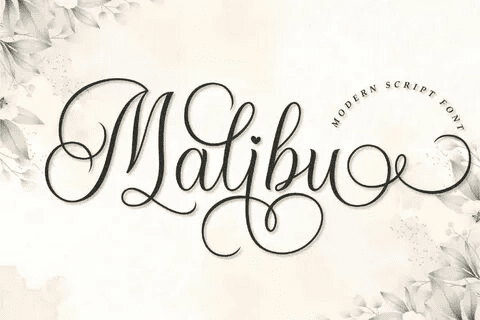
Название: Malibu Font
Малибу - это элегантный рукописный шрифт.
Влюбитесь в его невероятно универсальный стиль и используйте его для создания эффектных дизайнов!